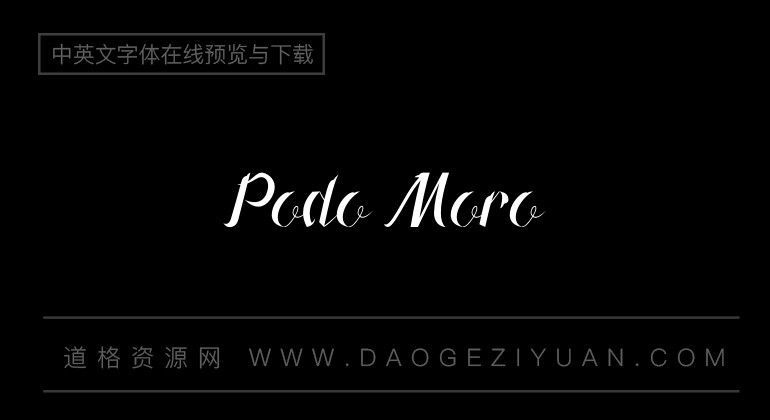
Podo Moro
Podo Moro 是一款极具特色的复古字体,它以古典文字模仿的方式创作而成,结合了古老的文字及现代化的设计元素。字体采用曲线线条,有宽度变化,特别适合用于报刊、书籍、海报、网页等多种场合。Podo Moro 字体的特点是它的字体结构清晰,笔画细腻,给人以温柔而又充满灵气的感觉,使用它来排版文字,可以给文字以更多的艺术感。
Podo Moro是一款非常不错的手写艺术字体,具有很好的视觉感,适合于文化类的宣传设计、商业类品牌的广告和产品包装设计以及个性化文字排版等较多场景。